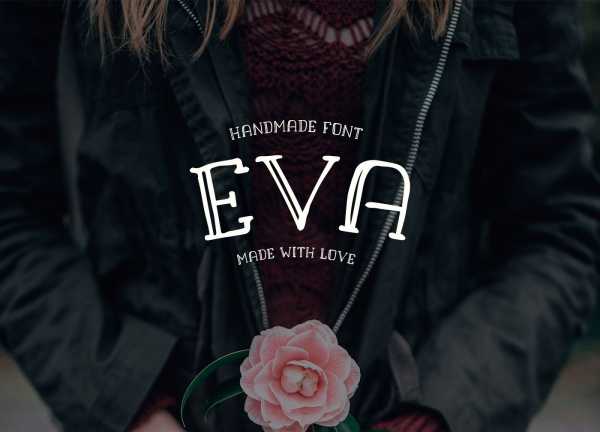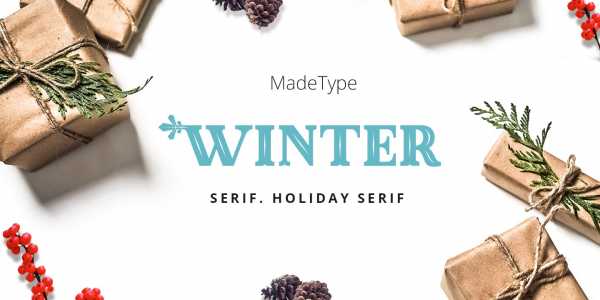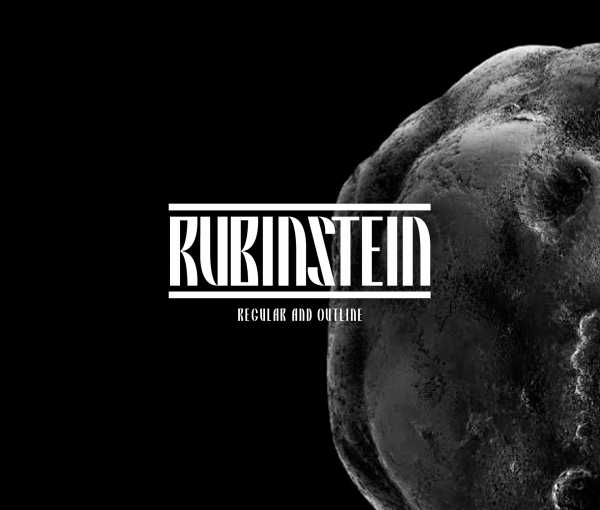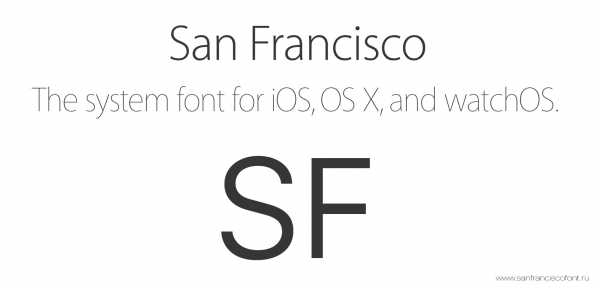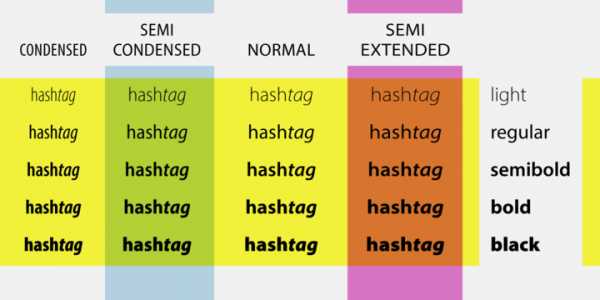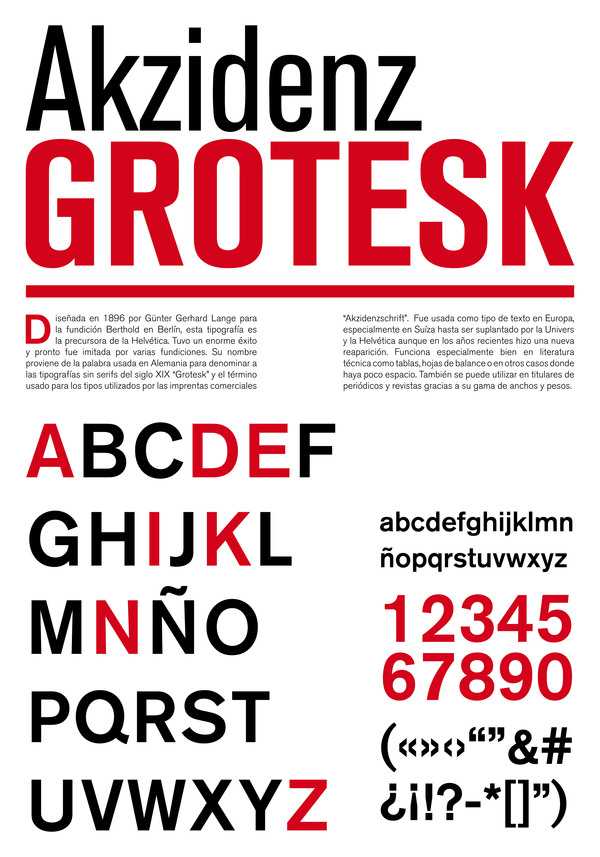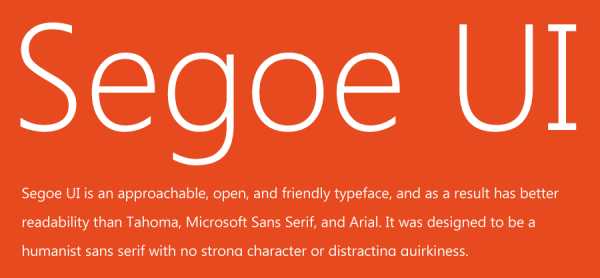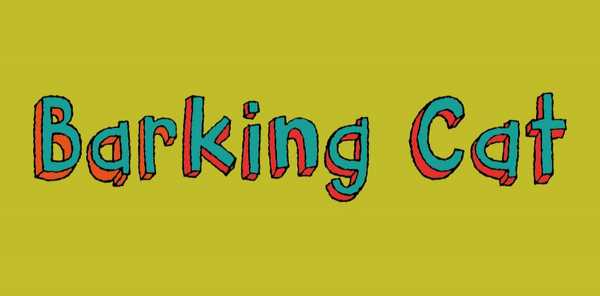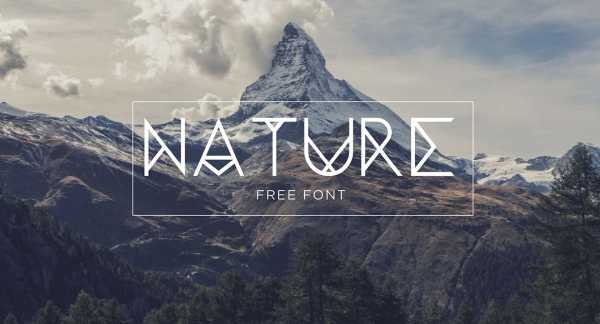
Модный шрифт 2019 кириллица – 9 креативных трендов шрифтов на 2019 год
9 креативных трендов шрифтов на 2019 год
Вложение красивой типографии в ваш дизайн является одним из наиболее эффективных способов общения как бренда. Вот почему соблюдение последних тенденций шрифтов абсолютно необходимо.
Творческие шрифты не только несут ваше сообщение, но также оказывают визуальное воздействие и вызывают эмоции. Типография может выражать радость или страх, громкий или тихий. Или это может заставить вас смеяться, съеживаться, задыхаться и все между ними.
Давайте посмотрим на последние тенденции шрифтов в 2019 году, поэтому вы можете использовать их в своих собственных проектах.
9 шрифтовых тенденций, которые будут огромными в 2019 году
1. Экстра-громкие жирные шрифты
2. Минимальные шрифты без засечек
3. Ностальгические старинные шрифты
4. Расширяющиеся шрифты скриптов
5. Контурные шрифты
6. Высококонтрастные шрифты с засечками
7. Причудливые шрифты
8. Мессиальные шрифты
9. Уникальная ручная надпись
1. Экстра-громкие жирные шрифты
Смелые шрифты заставляют ваш логотип всплывать на все, что вы наделите. Плакаты и флаеры будут видны издалека. И ваш сайт будет заполнен тонной личностью.
Красивый веб-сайт с использованием смелого и громкого шрифта. Via Van Holtz Co. Прекрасный пример жирного шрифта, используемого для брендинга по I n f r. Большое использование жирного шрифта на плакате от jestyr372. Минимальные шрифты без засечек
Встречайте интровертированных братьев и сестер смелой типографии: простые шрифты без засечек (это шрифты без засечек, маленькие ноги на углу каждой буквы), которые по-прежнему будут огромным фаворитом для минималистических проектов в 2019. Благодаря своей простоте эти шрифты невероятно просты в работе. Они не являются визуально сложными и очень эффективны при использовании хорошо.
Простые без засечек делают композиции выглядящими воздушными и мягкими с чувством покоя и спокойствия. Дайте им место для дыхания и пространства, в котором они нуждаются, или вы рискуете убрать их очарование.
Отличный пример чистого, но столь мощного веб-сайта. Via Libratone. Прекрасный пример простого шрифта без засечек, используемого в дизайне упаковки Стэном Куркулой Красивый пример дизайна логотипа, в котором используется шрифт без засечек Ян Дуглас Такой симпатичный дизайн, используя только простой без засечек. Via Un Barco. Идеальный и яркий пример того, чтобы дать элементам дышать. Via DixonBaxi.3. Ностальгические старинные шрифты
Чем больше мы погружаемся в будущее, тем более привлекательным становится прошлое. Это касается моды, дизайна интерьера и да, графического дизайна. Поэтому неудивительно, что в 2019 году мы увидим множество шрифтов, имитирующих и пытающихся вернуть прошлое.
Использование старинных шрифтов может сделать дизайн логотипа или пакета элегантным и серьезным. Или смелый, но ностальгический и запутанный. Если вы хотите привнести классический штрих в современный мир, этот стиль определенно для вас.
Удивительный семейство шрифтов с сочетанием современного с винтажем. Via Ilham Herry. Такой подробный и красивый пример винтажного шрифта в действии от Sign²in4. Расширяющиеся шрифты скриптов
Сценарии шрифтов никогда не устаревают. Они имитируют текучесть почерка и строятся на элегантных буквенных формах каллиграфов. Тем не менее, шрифты скриптов сильно изменились, и в 2019 году они появятся в разных формах и стилях. Они могут быть классическими или причудливыми, серьезными или игривыми, монолинами или разнообразным весом. Когда дело доходит до шрифтов шрифтов, что-то идет в этом году. Независимо от того, какой стиль вы выберете, визуальный результат будет наполнен чувством удивления.
Элегантный, но причудливый шрифт, используемый в дизайне логотипа Yokaona Великолепный шрифт шрифта для монолинных шрифтов. Via Martina Flor. Современный логотип с использованием шрифта monoline script :: scott :: Отличный пример более современного разнообразного сценария. Via Menta.5. Контурные шрифты
Хотите ли вы накачать свой заголовок, выделить какую-то копию или сделать композицию воздушной, набросайте шрифты, которые вы покрыли, и они появятся повсюду в этом году. Их современный, индустриальный взгляд заставляет бренды выглядеть передовыми и зрелыми. Ищите их во всех видах разных форм и размеров: больших или малых, обычных или жирных, сгущенных или курсивных, деревенских и ручных или гладких и острых.
Красивый заголовок веб-сайта с использованием выделенного шрифта простейшим ™ Прекрасный пример обложенного шрифта, используемого для дизайна логотипа goopanic 6. Высококонтрастные шрифты с засечками
Высококонтрастные засечки громкие, но элегантные, а в 2019 году они будут повсюду. Вы узнаете их чрезвычайно контрастные веса: восхождение на букву обычно тоньше, чем в нисходящем, и эти шрифты преувеличивают это различие, создавая драматический эффект.
Этот контраст делает их очень смелыми, вроде сырыми, с элементами «фантазии». Когда вы используете этот стиль оформления, вы легко сможете классифицировать свой дизайн.